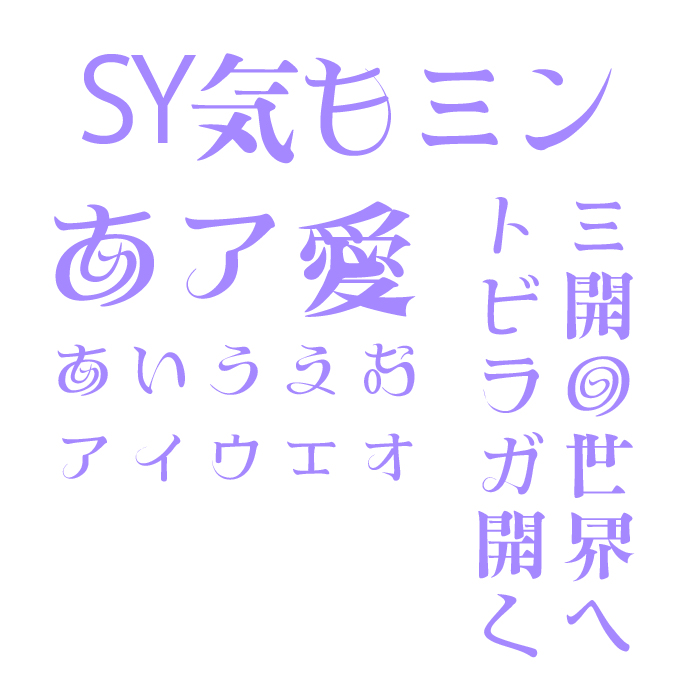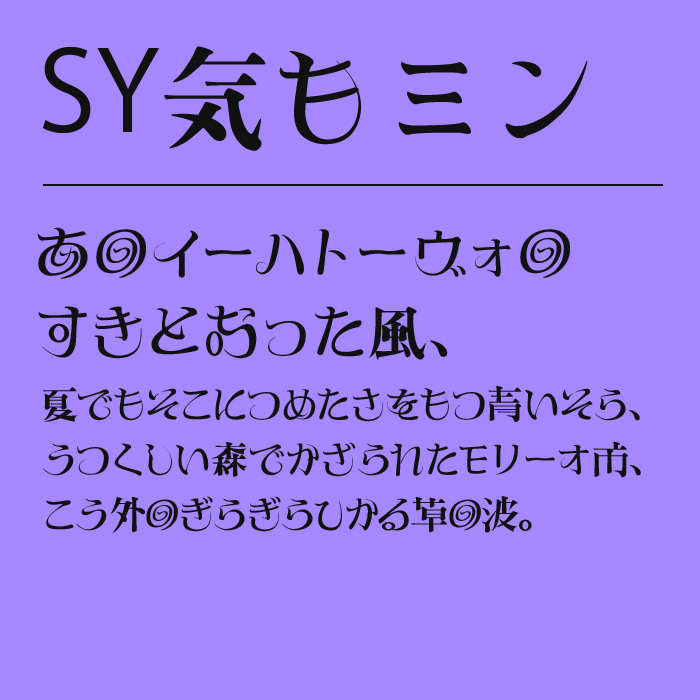
SY気もミンフォントは、明朝の骨格に遊びのあるうろこ・カール・渦を織り込んだ少し変わった明朝体フォントです。
縦画は端正、終筆でふっと巻く独特の装飾が、可憐さと気取りのあいだに立ちます。
レトロ香水や洋菓子、占いやファンタジー文庫など“軽やかに上品”を目指す題材にぴったりです。、文字自体が装飾として機能しているので、そのままベタ打ちだけでも雰囲気がでるフォントです。